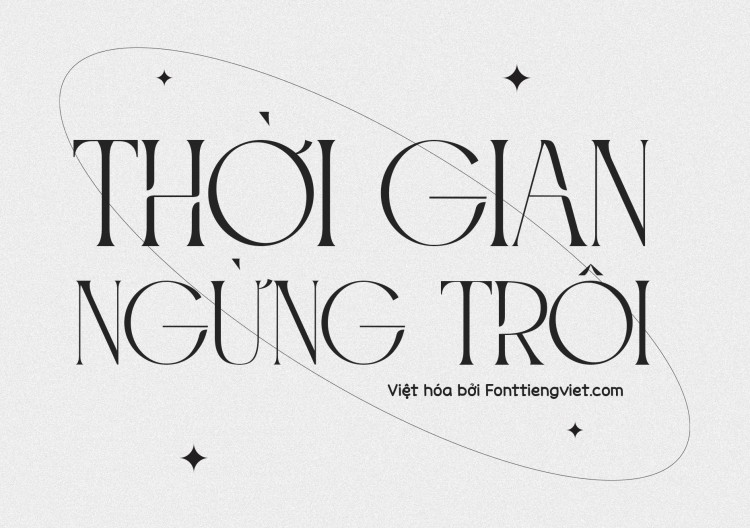
Font Việt hóa TF Henotica – Nhiều Glyphs đẹp
Font Việt hóa TF Henotica là một trong những lựa chọn hàng đầu cho các thiết kế đẳng cấp và sang trọng. Với bộ glyphs đa dạng và đẹp mắt, Henotica mang đến sự tinh tế ngay cả trong từng chi tiết nhỏ, giúp nâng tầm cảm xúc thẩm mỹ cho mọi sản phẩm.
Henotica rất phù hợp cho các thiết kế liên quan đến spa, chăm sóc sắc đẹp, và những lĩnh vực yêu cầu sự sang trọng. Đường nét thanh lịch của font chữ này không chỉ tạo nên ấn tượng mạnh mẽ mà còn gợi cảm giác thư giãn và dễ chịu, hoàn hảo cho không gian thương hiệu của bạn.
Sự kết hợp giữa vẻ đẹp và tính ứng dụng của Henotica chính là lý do khiến nó trở thành lựa chọn lý tưởng cho những ai muốn tạo dựng phong cách riêng biệt. Hãy sử dụng font chữ Henotica trong các thiết kế của bạn, để mang lại trải nghiệm tuyệt vời và hấp dẫn cho khách hàng!